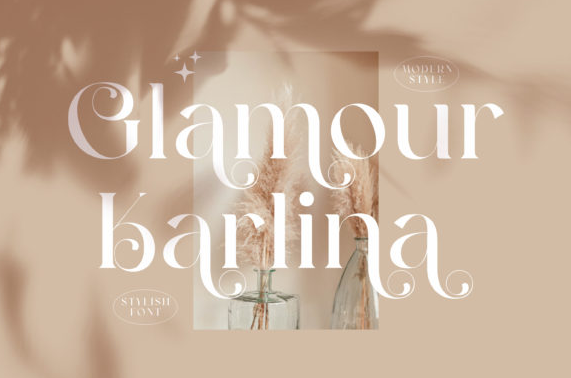
[Creativefabrica] Glamour Karlina Font (2021)
Glamour Karlina - это современный классический шрифт с засечками, который выглядит неповторимо торжественно и стильно одновременно. Это отличный выбор для роскошных логотипов, изысканных брендов, модного брендинга, цитат и многого другого! Этот шрифт закодирован в PUA, что означает, что вы можете легко получить доступ ко всем глифам и штрихам!